Font VNF (Vietnamese Font) là hệ thống các bộ phông chữ được cộng đồng designer Việt Nam tối ưu hóa riêng cho bảng mã tiếng Việt, giúp khắc phục triệt để các rào cản về hiển thị dấu thanh trong thiết kế đồ họa. Với sự đa dạng từ các dòng phông hiện đại, tối giản đến các kiểu chữ nghệ thuật cá tính, việc sở hữu trọn bộ tài nguyên này giúp các kiến trúc sư và nhà thiết kế trình bày hồ sơ dự án, phối cảnh công trình một cách chuyên nghiệp và mạch lạc.
Khám phá sự đa dạng và tính thẩm mỹ của kho tài nguyên font VNF Việt hóa
Khác với các bản phông chữ quốc tế thường gặp lỗi “nhảy dấu” hoặc dấu bị quá nhỏ, các mẫu chữ trong bộ sưu tập VNF mang lại sự đồng bộ thị giác ấn tượng trên mọi trang văn bản. Sự phong phú về chủng loại từ Sans-serif vững chãi đến Script mềm mại cho phép người dùng linh hoạt thay đổi ngôn ngữ thiết kế theo từng hạng mục công trình cụ thể.
Sự ổn định của bộ phông này còn nằm ở khả năng tương thích cao với các phần mềm chuyên dụng trong ngành xây dựng. Dù bạn đang làm việc trên bản vẽ AutoCAD hay trình bày slide thuyết trình dự án nhà lắp ghép, các nét chữ vẫn giữ được độ rõ nét và nhịp điệu riêng biệt. Đây là phương án hiệu quả để thể hiện tư duy tổ chức thông tin khoa học, giúp truyền tải thông điệp về sự chỉn chu và năng lực chuyên môn của đơn vị thiết kế đối với khách hàng và đối tác.
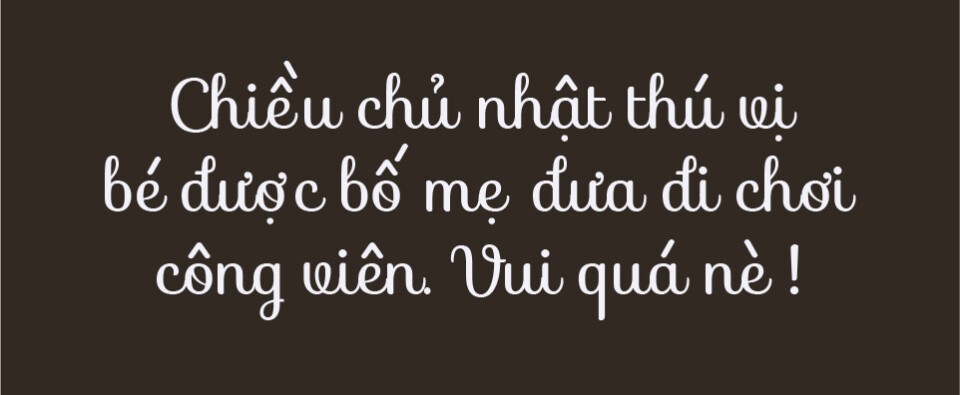
Gợi ý lựa chọn: Để đạt hiệu quả thị giác ổn định cho hồ sơ năng lực, bạn nên sử dụng các dòng VNF không chân cho phần nội dung thuyết minh và phối hợp cùng các dòng VNF có chân cho các tiêu đề chương. Sự tương phản này giúp bản thiết kế của bạn trông chuyên nghiệp và dễ theo dõi hơn.
03 Ứng dụng đưa phông chữ VNF vào thực tế triển khai công trình
Nhờ diện mạo đa dạng và khả năng nhận diện cao, việc sử dụng các mẫu chữ từ bộ tải font VNF Việt hóa mang lại giá trị thực tế lớn trong khâu quảng bá và hoàn thiện các dự án xây dựng:
- Hệ thống nhận diện cho Homestay & Cafe: Sử dụng các dòng phông nghệ thuật trong bộ VNF cho biển tên phòng hoặc menu giúp không gian nghỉ dưỡng toát lên vẻ thư thái và có gu thẩm mỹ riêng, thu hút khách hàng ngay từ khi bước chân vào khu nhà lắp ghép.
- Trình bày hồ sơ kỹ thuật chuyên sâu: Độ sắc sảo của các phông chữ kỹ thuật trong bộ VNF hỗ trợ đắc lực cho kiến trúc sư khi trình bày các ghi chú vật liệu panel, thông số kết cấu thép, giúp bản vẽ trông sạch sẽ và chuyên nghiệp hơn.
- Thiết kế biển hiệu văn phòng container: Những nét chữ hiện đại và vững chãi của dòng VNF Sans-serif rất ăn ý khi gia công chữ nổi laser trên mica hoặc inox, giúp việc nhận diện thương hiệu công ty trở nên dễ dàng và đẳng cấp.
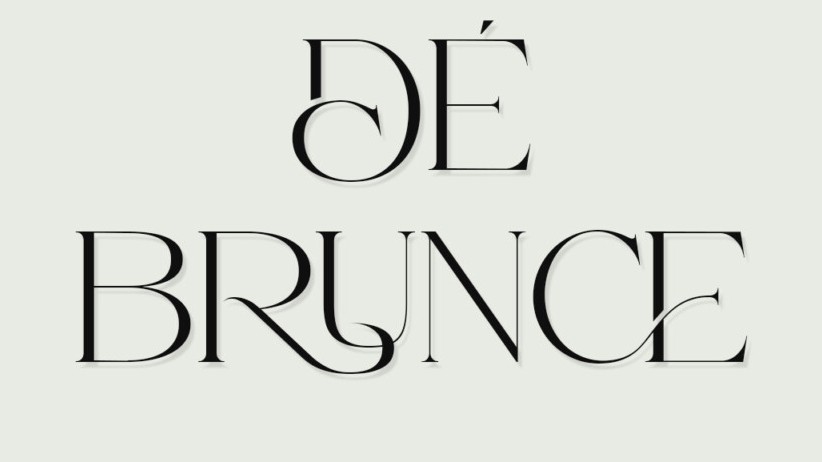
03 Lưu ý để bố cục phông chữ VNF đạt độ rõ nét cao
Để khai thác hiệu quả vẻ đẹp của dòng phông đa năng này mà không làm rối mắt người xem, người thiết kế nên lưu tâm một số lưu ý kỹ thuật sau:
- Kiểm soát khoảng cách dòng Với các dòng phông VNF có cấu trúc ký tự đầy đặn, bạn nên thiết lập khoảng cách dòng thoáng một chút để văn bản không bị bết dính, giúp người đọc cảm thấy thoải mái khi tiếp nhận nội dung dài.
- Lựa chọn độ đậm phù hợp: Hãy tận dụng các biến thể Bold cho các con số hoặc thông tin quan trọng trong dự toán công trình để tạo độ nhấn thị giác mạnh mà không cần sử dụng quá nhiều màu sắc gây nhiễu.
- Tính đồng bộ trong hệ thống tài liệu: Hãy duy trì sử dụng một nhóm phông VNF xuyên suốt từ bản vẽ AutoCAD đến slide trình chiếu và hồ sơ báo giá gửi khách hàng để tạo nên sự nhất quán trong hình ảnh thương hiệu chuyên nghiệp của đơn vị thi công.